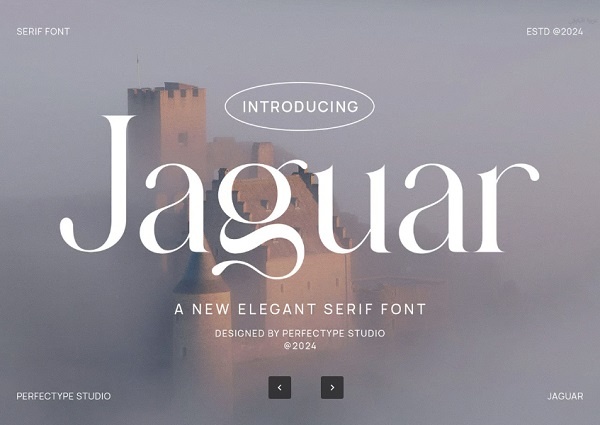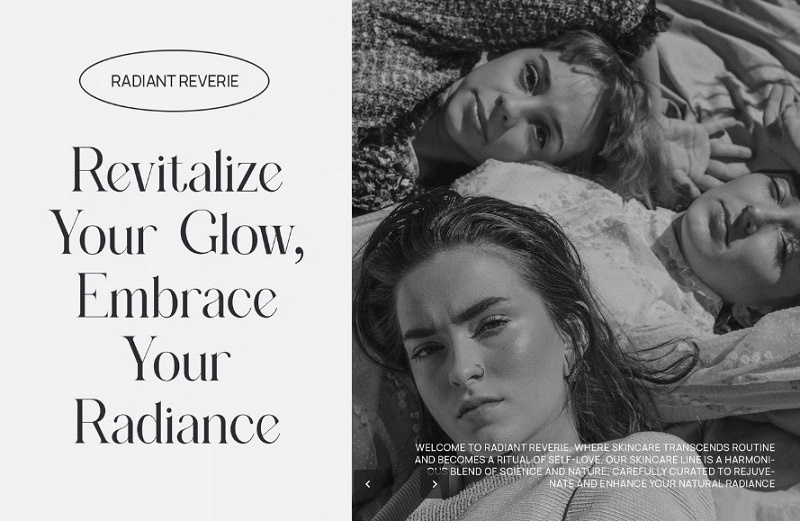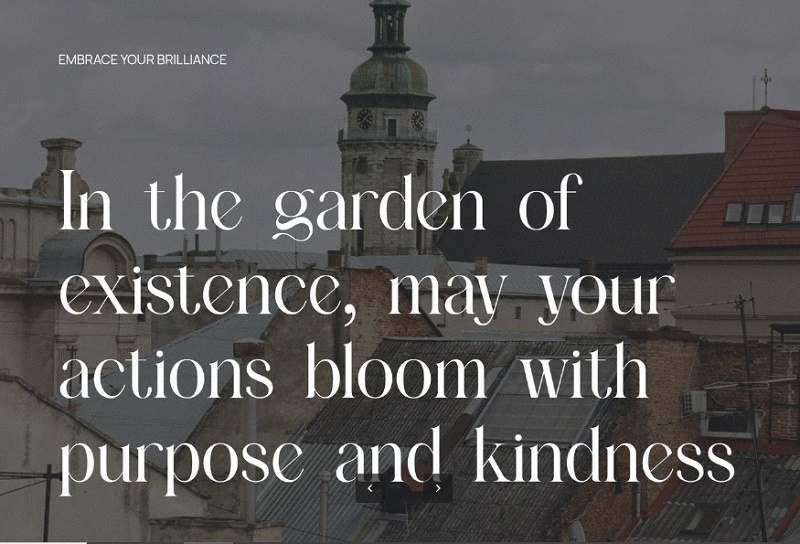
دانلود فونت انگلیسی Jaguar
دانلود فونت انگلیسی Jaguar از جی اف ایکس دانلود. یک فونت منحصر به فرد و بسیار زیبا که برای طراحی برند و لوگو، طرح های عروسی، پست های شبکه های اجتماعی، تبلیغات، بسته بندی محصولات و هر پروژه ای که به فونت جذاب نیاز داشته باشد، مناسب است. این فونت شامل فایل های OTF/TTF/WOFF می باشد.
فونت انگلیسی Jaguar
فونت زیبای انگلیسی Jaguar